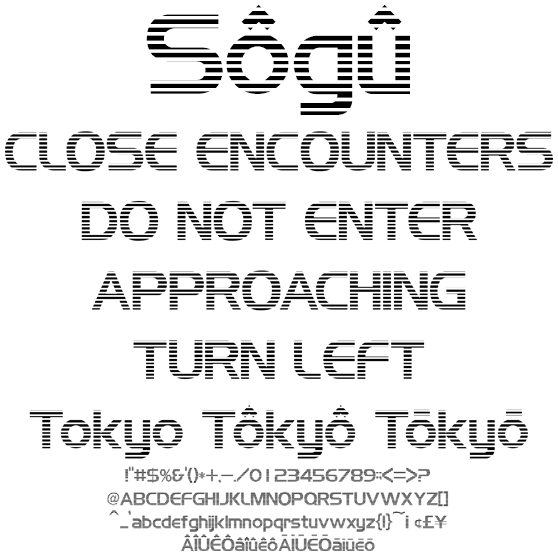
接近遭遇欧文 AFCloseEncounters3
AFCloseEncounters3
接近遭遇しそうなスリット入りな欧文フォント。AFCloseEncounters2より太めのスリットを入れることで、隙間が広がり指定色が緩和されます。目立ちながらもバックカラーの同化を目指しました。警告表示、案内メッセージ、ブリンクさせるアイキャッチ、注目させたいワードや大見出しにお使いください。